东汉《高颐西阙/què/》又名《益州太守高颐西阙》,隶书,线装,剪裱,墨纸尺寸:11x13cm,原刻清末拓本,北京图书馆藏。旧托整纸四张,拓法新颖,书法古朴。尺寸143*51厘米。见《中国历代石刻拓本汇编:高颐西阙隶书原刻》。
高颐阙为最著名的汉阙之一,其书法和艺术价值丰常重要,阙在四川雅安。高颐阙,东汉益州太守高颐及其弟高实的墓阙,四川保存最完整、最精美的石阙,在雅安市姚桥镇,东汉建安十四年(209年)建造。分东西阙,东阙为"汉故益州太守武阴令上计史举孝廉诸部从事高君字贯方",西阙为"汉故益州太守阴平督尉武阳令北府丞举孝廉高君字贯光"。是研究汉代书法艺术,建筑艺术、造型艺术、地震史的珍贵文物。高颐阙位于雅安市城市建设新区,成都至雅安高速公路金鸡关出口处,雅安汉阙博物馆所在地。
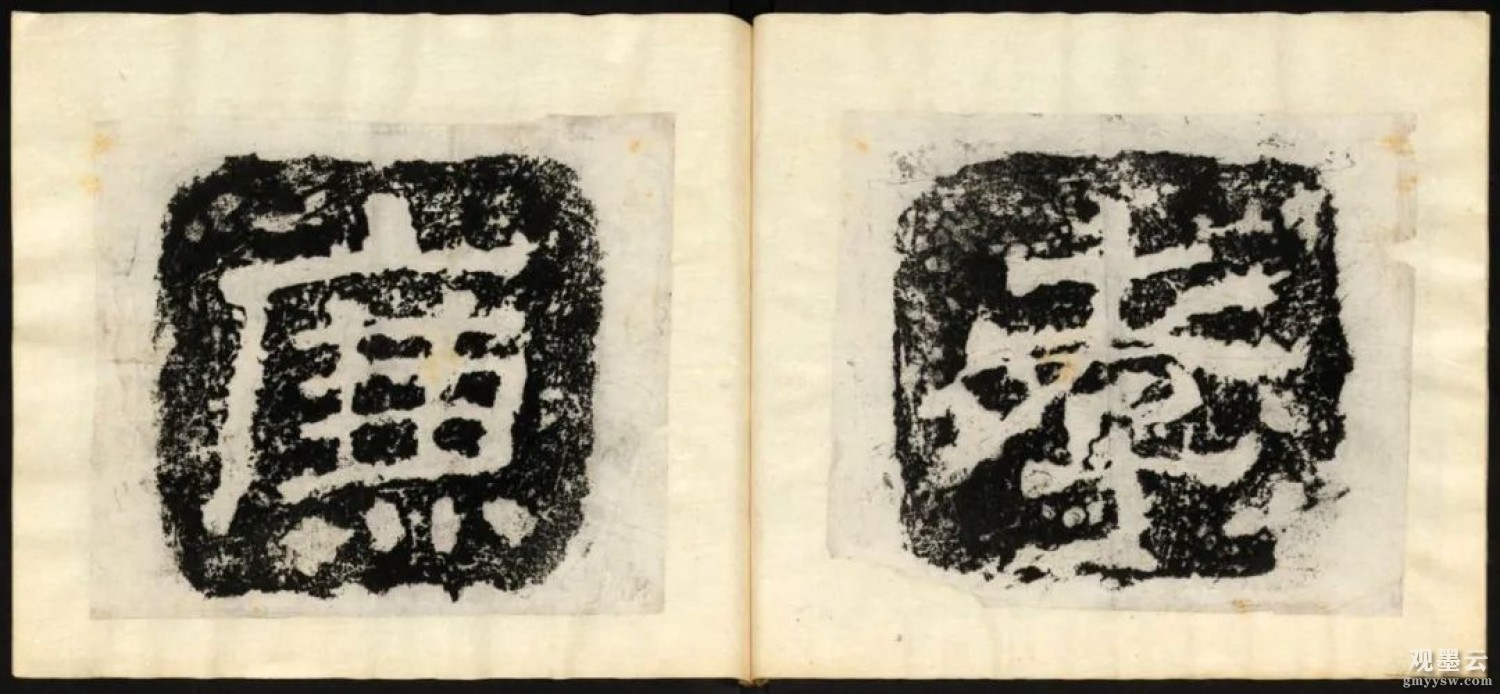
汉阙是中国古代特有的建筑设施,是汉代宫殿、祠庙和陵墓前一种表示尊严的装饰性建筑,每阙由主阙和子阙组成,一般有阙墓、阙身、阙顶三部分,既是一种古老的建筑艺术,又是一种特殊的石刻珍品,是研究当时历史文化、建筑、雕塑、美术的重要实体。
【释文】《益州太守高颐双阙模本》汉故益州太守阴平督尉武阳令北府丞举孝廉高君字贯光。
::益州(yì zhōu ) 中国古地名,汉武帝设置的十三州(十三刺史部)之一。
::高颐(gāo yí ) 今四川雅安市雨城区人,出生年月不详-209年,字贯光,东汉末与其弟实同举孝廉,历任北府丞,武阳令、阴平都尉及盆州太守。
::模本(mó běn ) 照书画原件临摹或翻刻拓印的复制品。
::督尉(dū wèi ) 官名,次于将军的军官。
::举孝廉(jǔ xiào lián ) 举孝廉是汉朝的一种由下向上推选人才为官的制度,孝廉是察举制的主要科目之一。被举人的资历,大多为州郡属吏或通晓经书的儒生。
【1】《益州太守高颐双阙模本》
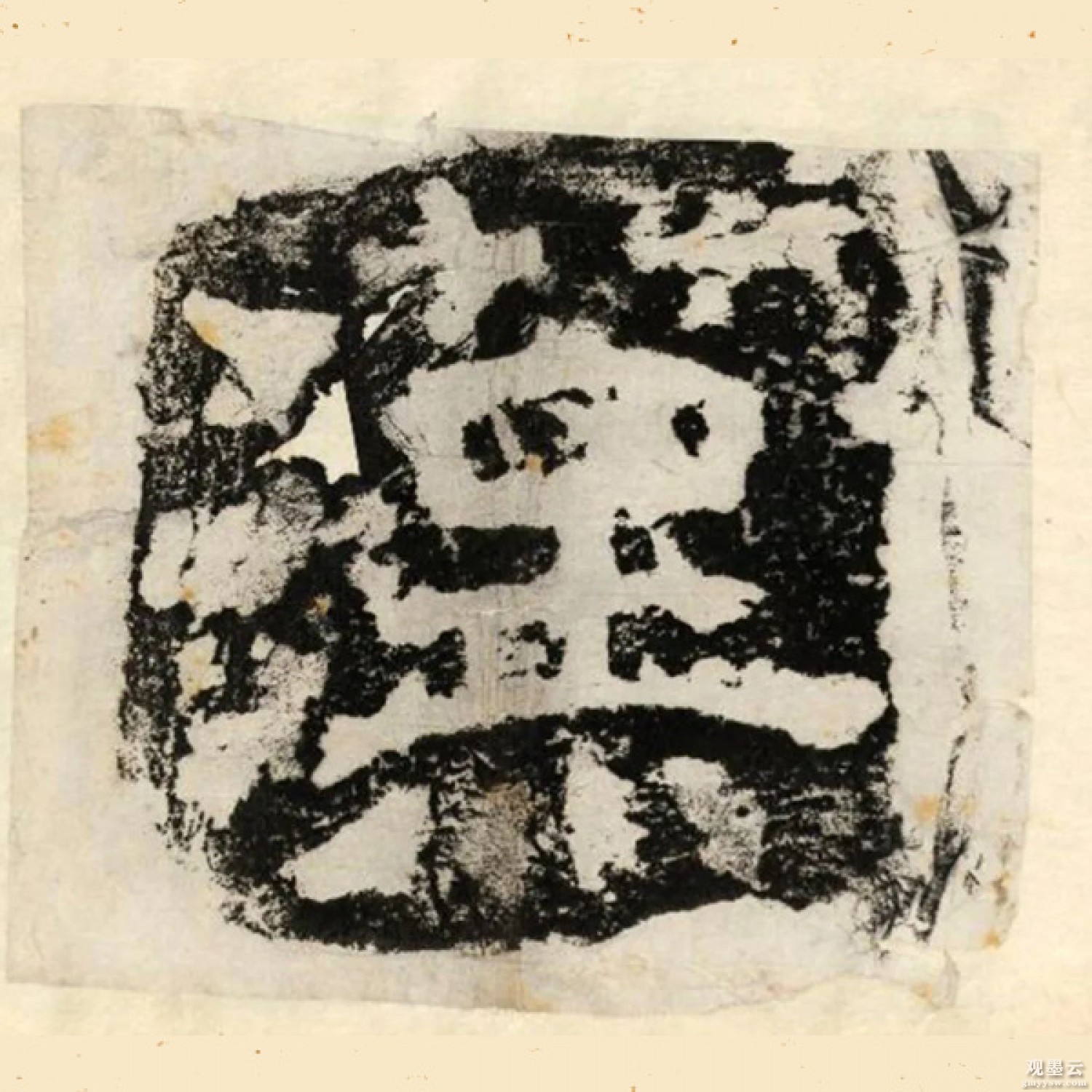
【2】汉
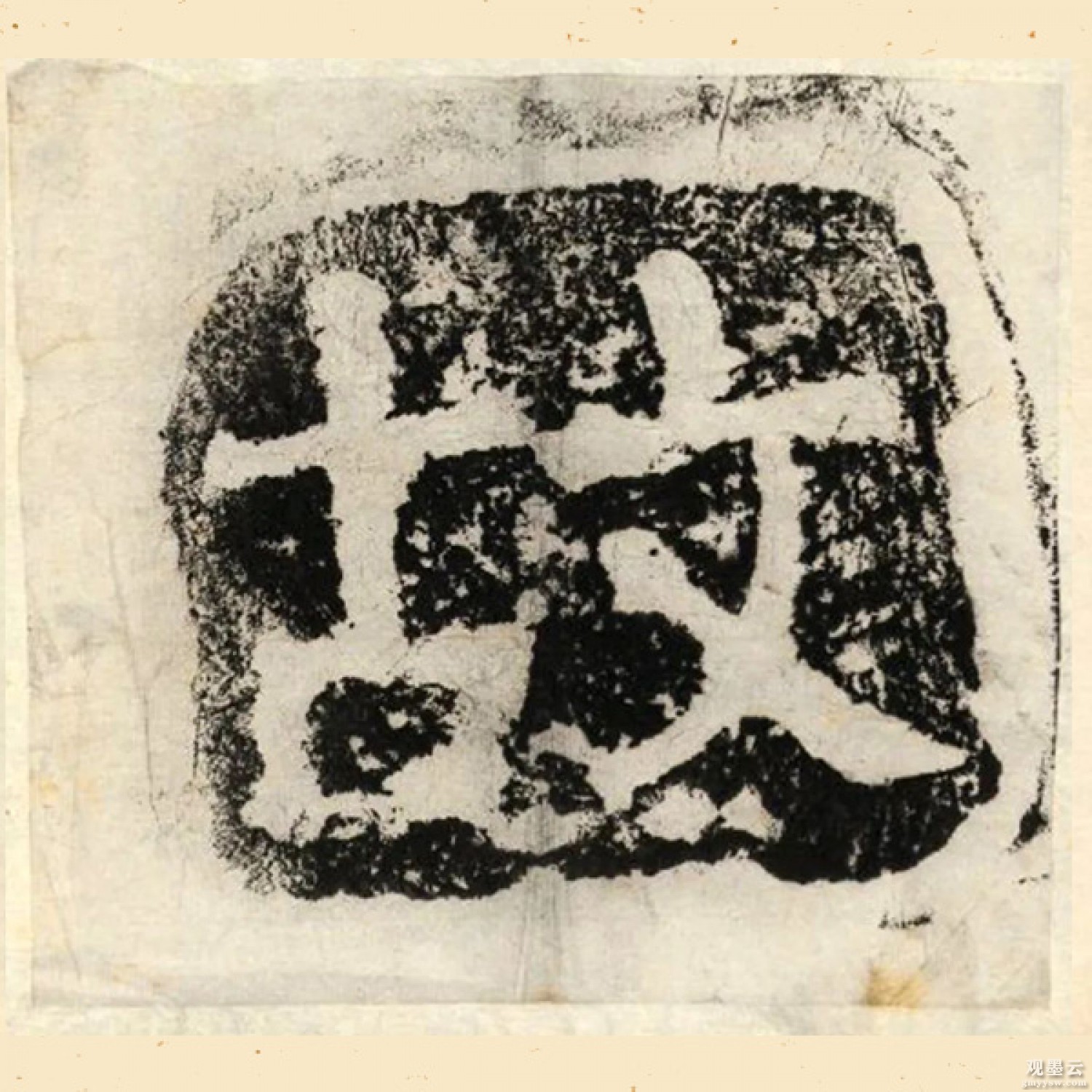
【3】故
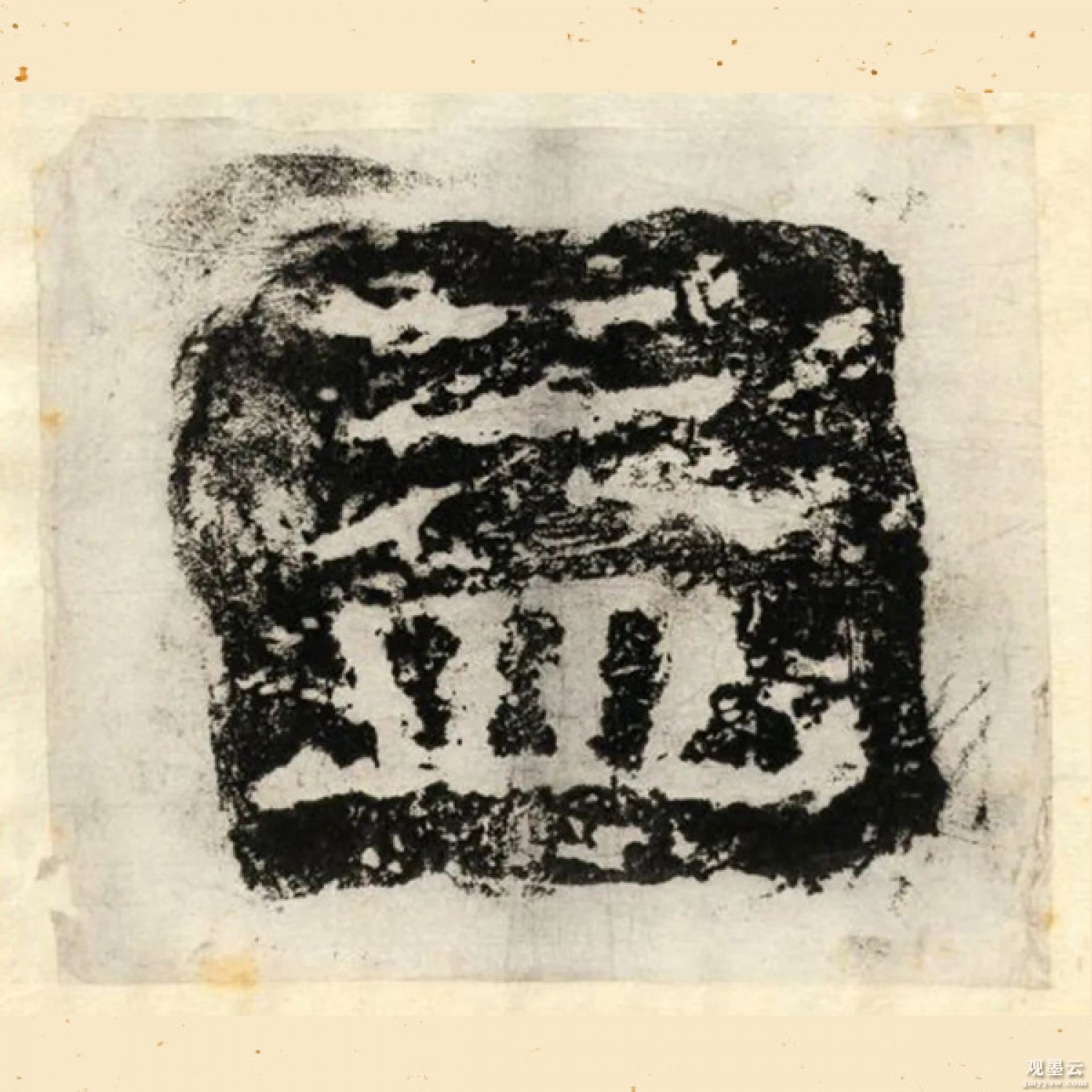
【4】益
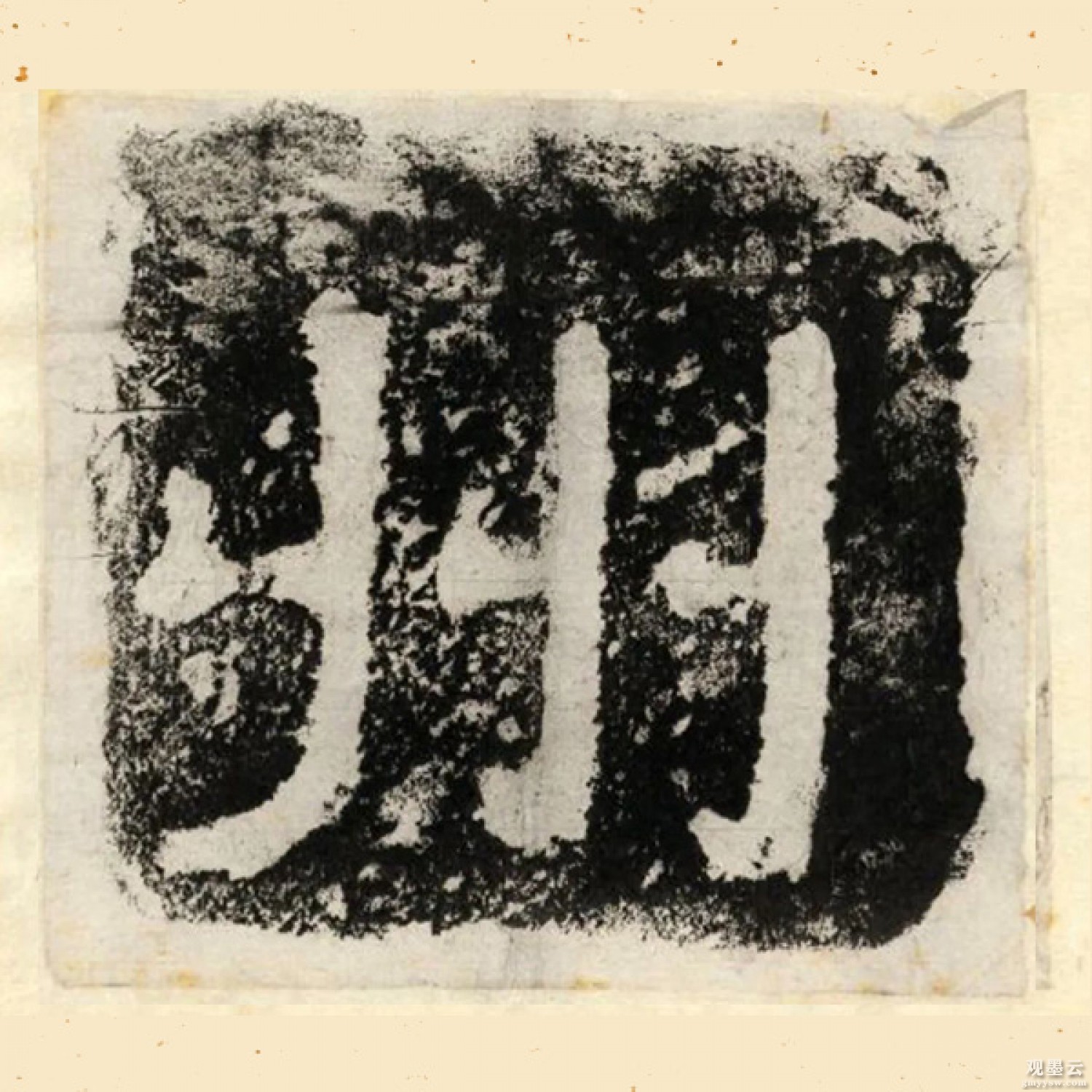
【5】州
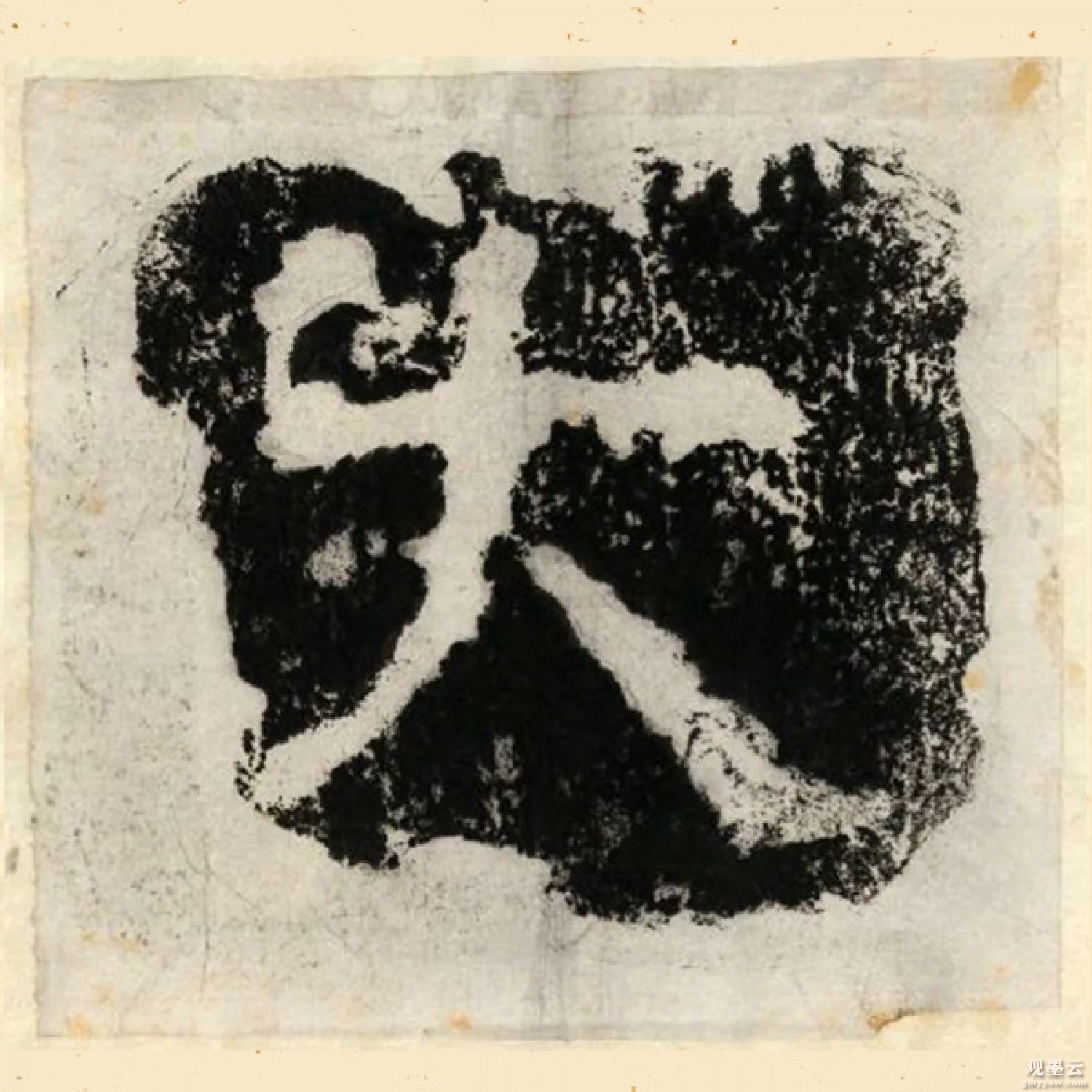
【6】太
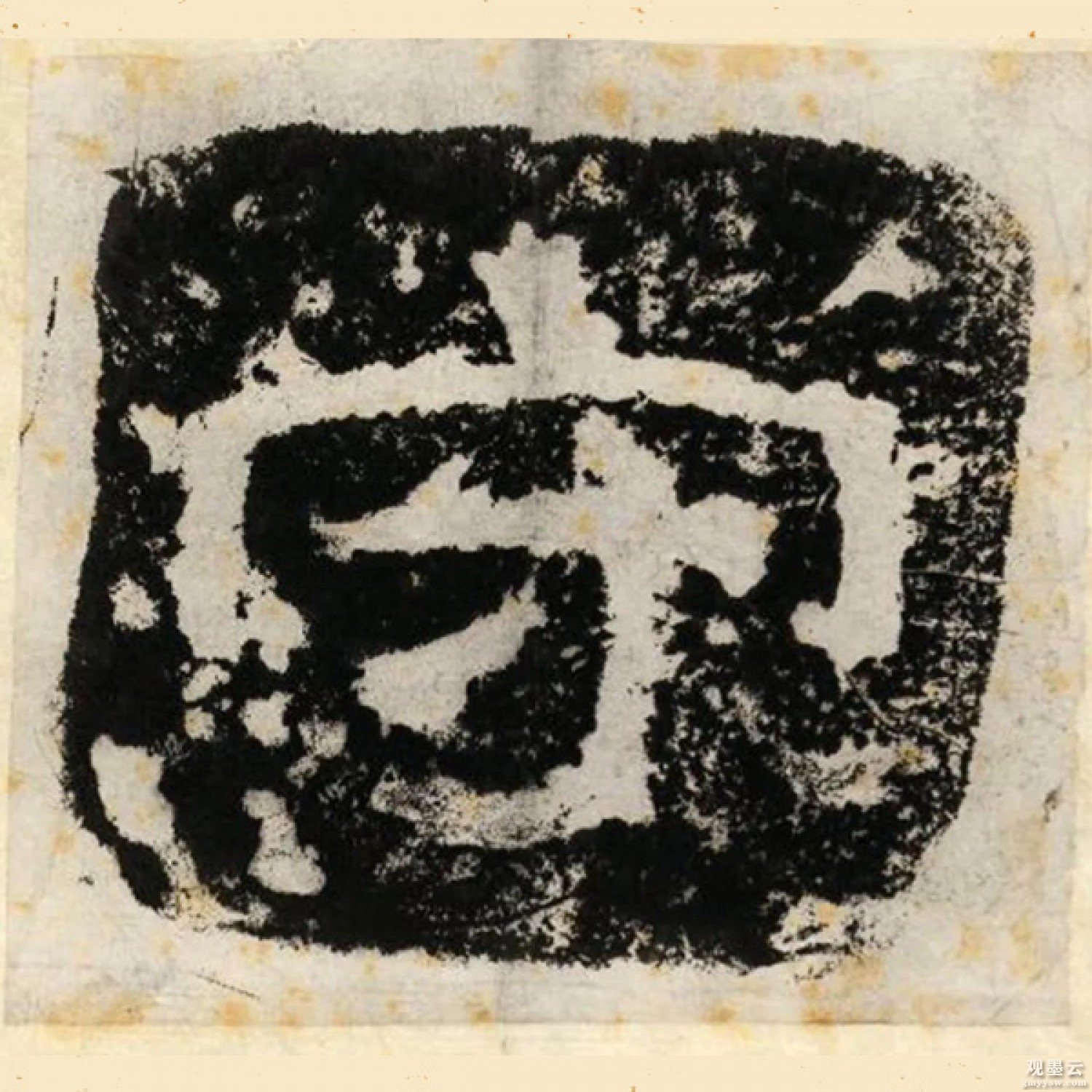
【7】守
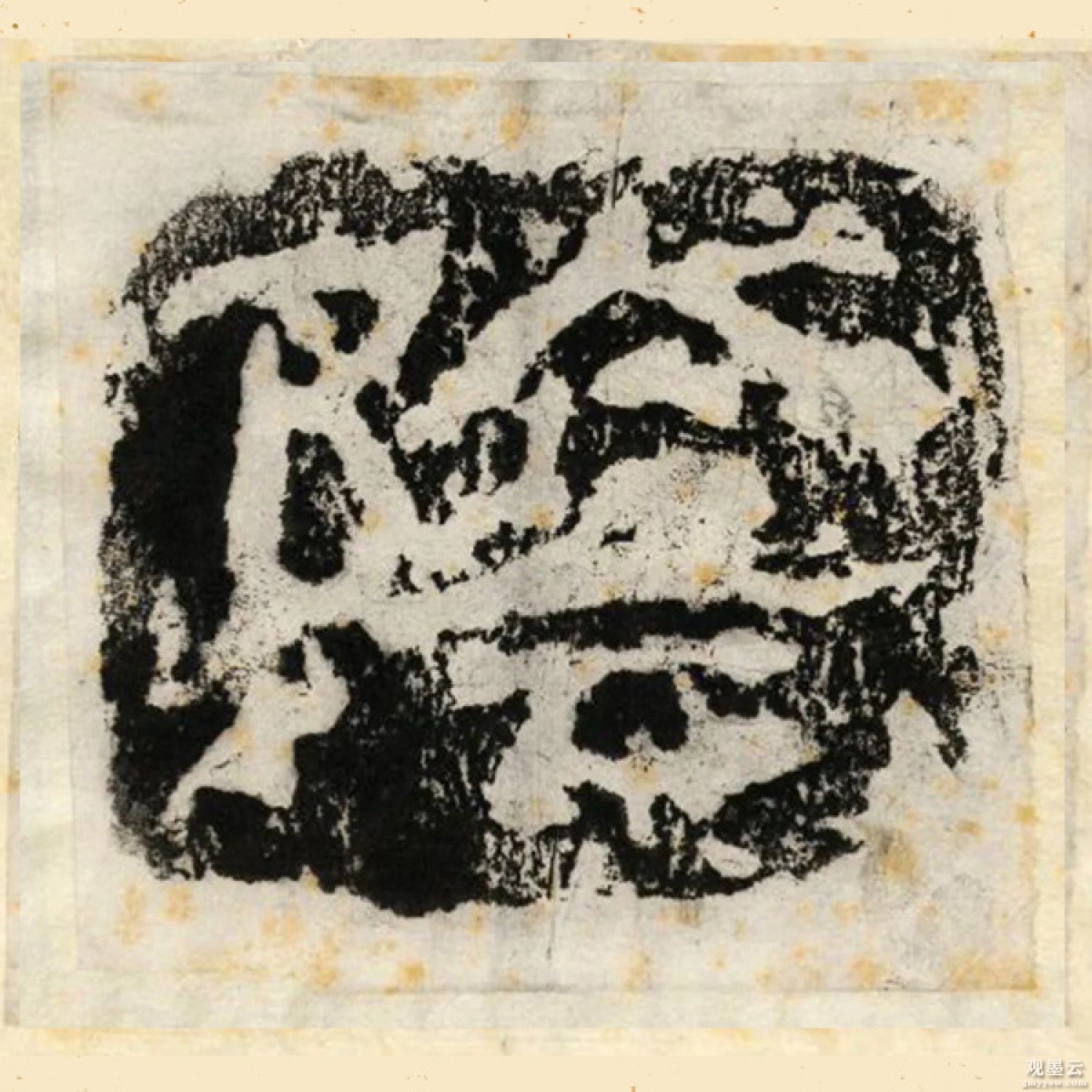
【8】阴
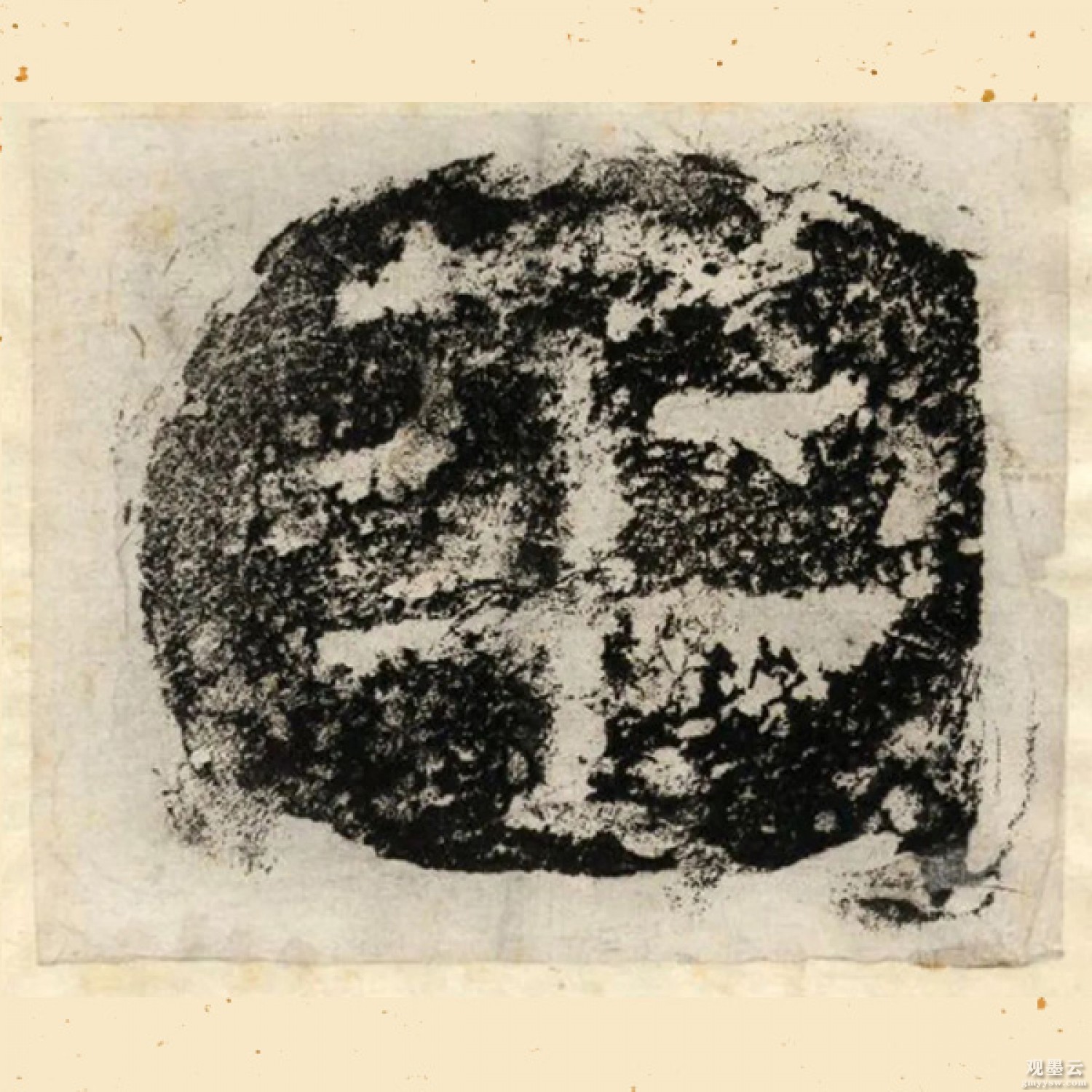
【9】平
【10】督
【11】尉
【12】武
【13】阳
【14】令
【15】北
【16】府
【17】丞
【18】举
【19】孝
【20】廉
【21】高
【22】君
【23】字
【24】贯
【25】光